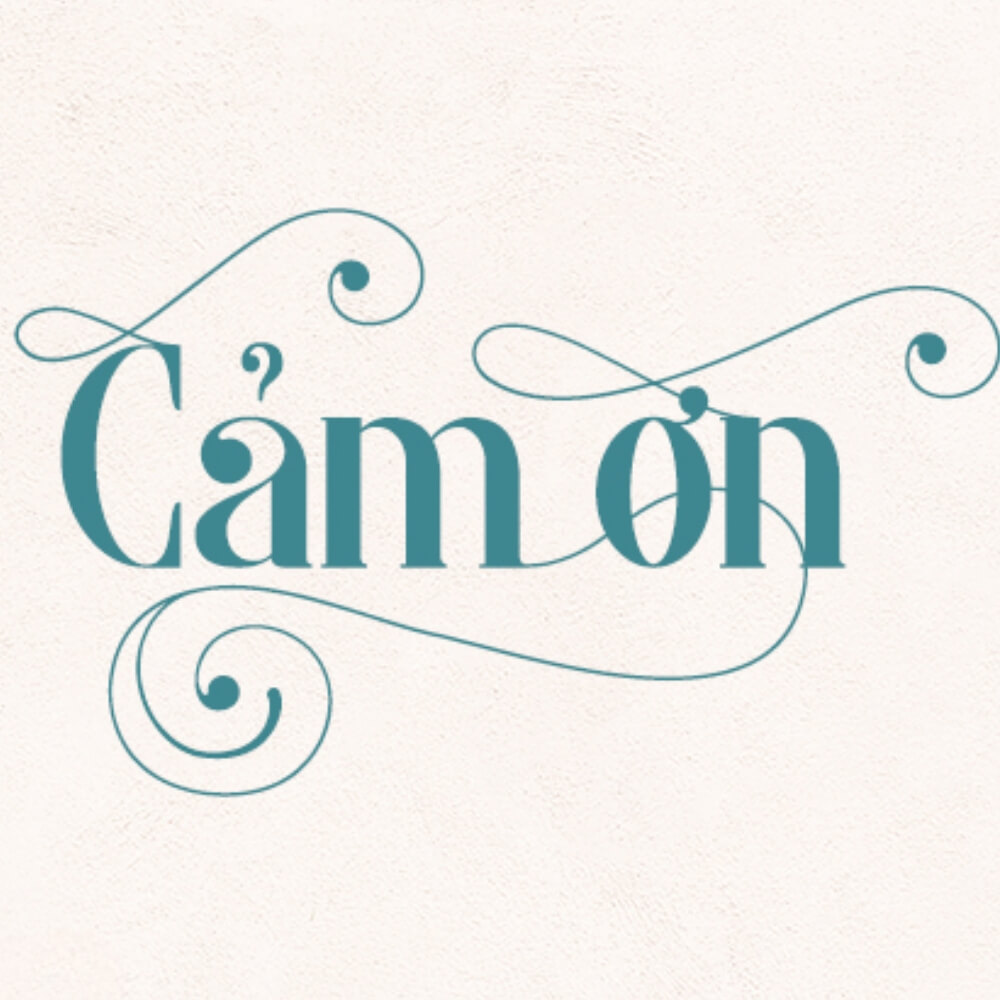
Font việt hoá SVN Morva là font serif có nét chân đặc biệt và họa tiết xoáy trang trí, tạo ra sự kết hợp hiếm gặp giữa tinh tế và cá tính phù hợp với thiết kế đám cưới, logo thương hiệu minimalist và header website. Bài viết này, In Viva sẽ cung cấp link tải font việt hóa SVN Morva cùng hướng dẫn ứng dụng thực tế trong thiết kế và in ấn nhé!
Đặc điểm của font SVN Morva
SVN Morva do Alit Suarnegara thiết kế, phát hành bởi Alit Design, Việt hóa bởi STYLEno.1 Fonts. Font thuộc nhóm serif display với hai yếu tố thiết kế đặc trưng kết hợp.
- Chân serif kiểu bracketed đặc biệt: không phải chân serif thẳng thông thường — Morva dùng bracketed serif (chân serif có đường cong kết nối với thân chữ) tạo ra cảm giác vừa cổ điển vừa tinh tế, khác biệt với phần lớn serif display trên thị trường.
- Họa tiết xoáy trang trí (swirl ornaments): một số ký tự trong Morva có thêm nét xoáy trang trí ở đầu hoặc cuối chữ, tạo điểm nhấn trang trí mà không cần thêm graphic bổ sung.
- Phong cách minimalist-elegant: dù có họa tiết, Morva không rườm rà — ngôn ngữ thiết kế tổng thể vẫn giữ sự đơn giản và thanh lịch, phù hợp với concept minimalist hiện đại.
- Chỉ có Regular: Morva là font đơn weight, không có Bold hay Italic. Sức hút nằm hoàn toàn ở dáng chữ và chi tiết trang trí.
Ứng dụng của font việt hoá SVN Morva trong thiết kế
Ứng dụng của font SVN Morva trong thiết kế rất đa dạng nhờ phong cách thanh lịch, hiện đại và dễ đọc, phù hợp từ tiêu đề, poster đến nhận diện thương hiệu.
- Thiệp cưới, invitation và ấn phẩm wedding: sự kết hợp giữa chân serif thanh và họa tiết xoáy tạo ra ngôn ngữ thiết kế đám cưới vừa trang trọng vừa hiện đại — phù hợp cho tên cặp đôi, tiêu đề thiệp và chương trình hôn lễ.
- Logo thương hiệu mỹ phẩm, thời trang và lifestyle: font phù hợp với các thương hiệu muốn định vị trong phân khúc từ mid đến premium, gợi cảm giác curated và tinh tế.
- Header website và landing page: ở cỡ lớn từ 48px trở lên, Morva tạo ra headline đẹp và khác biệt so với các font serif phổ biến như Playfair Display hay Lora.
- Bao bì sản phẩm cao cấp: nước hoa, sản phẩm chăm sóc da, thực phẩm premium — Morva cho thấy phong cách brand khi in trên chất liệu giấy mịn hoặc bìa cứng.
Gợi ý phối font: Morva (tiêu đề) + Be Vietnam Pro Light hoặc Lato Light (nội dung phụ) tạo ra hệ thống chữ cân bằng giữa cá tính và khả năng đọc.
Lỗi thường gặp khi dùng font việt hoá SVN Morva
Dưới đây là các lỗi thường gặp khi dùng font việt hoá SVN Morva mà bạn nên tránh để đảm bảo thiết kế luôn rõ ràng và chuyên nghiệp.
- Dùng Morva ở cỡ quá nhỏ khiến mất chi tiết trang trí. Họa tiết xoáy và chân serif đặc biệt của Morva chỉ hiện rõ từ 24pt trở lên khi in. Ở cỡ nhỏ hơn, font trông như serif thông thường và mất đi phần lớn điểm đặc trưng.
- Dùng font việt hoá Morva cho nội dung dài. Morva là display font thiết kế cho tiêu đề và điểm nhấn, không phải cho đoạn văn dài. Dùng cho body text gây mỏi mắt và trông không chuyên nghiệp.
- Nhầm SVN Morva với font tương tự rồi tải nhầm bản. Có nhiều font serif display có họa tiết xoáy trên thị trường. Khi tải, kiểm tra tên chính xác là SVN-MORVA và xem preview để xác nhận đúng dáng chữ cần dùng.